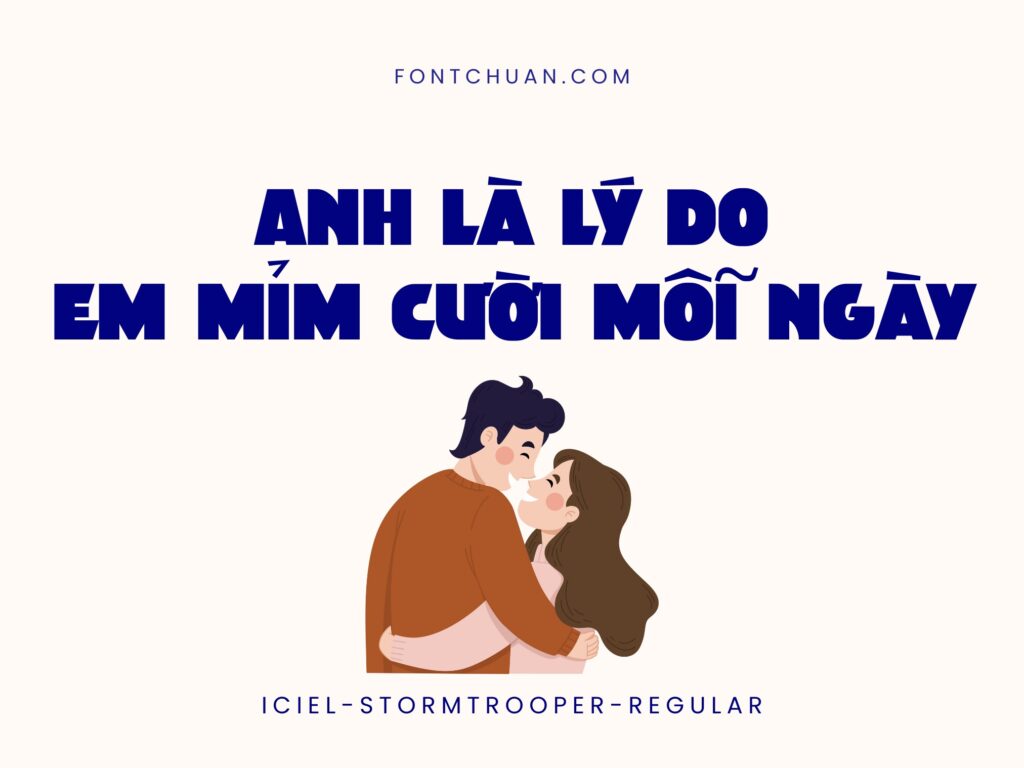
Font iCiel Stormtrooper Regular Việt Hóa
Tác giả Font: John Roshell
Việt hóa bởi: Iciel
Stormtrooper Regular là một kiểu chữ độc đáo được thiết kế bởi John Roshell, lấy cảm hứng từ các nhân vật Stormtrooper trong loạt phim Star Wars. Font này mang phong cách hiện đại, mạnh mẽ với các đường nét góc cạnh và sắc sảo, tạo cảm giác khoa học viễn tưởng và công nghệ cao. Đặc biệt, Stormtrooper Regular đã được Việt hóa bởi iCiel, hỗ trợ tiếng Việt cùng nhiều ngôn ngữ khác, đáp ứng nhu cầu đa dạng của người dùng. Font này được chia sẻ trên trang Font Tiếng Việt, giúp cộng đồng thiết kế ứng dụng dễ dàng trong các dự án của mình.
Về đặc điểm thiết kế, Stormtrooper Regular sở hữu các ký tự đậm, góc cạnh với cấu trúc hình học rõ ràng, tạo nên sự nổi bật và thu hút. Font này phù hợp cho các thiết kế như tiêu đề, poster, logo, bao bì sản phẩm và các ấn phẩm truyền thông liên quan đến chủ đề khoa học viễn tưởng, công nghệ và giải trí. Ngoài ra, Stormtrooper Regular còn thích hợp cho các ngành nghề như quảng cáo, công nghệ, giáo dục và bất động sản, cùng các sự kiện đặc biệt như lễ hội, sinh nhật, Halloween và Trung thu.